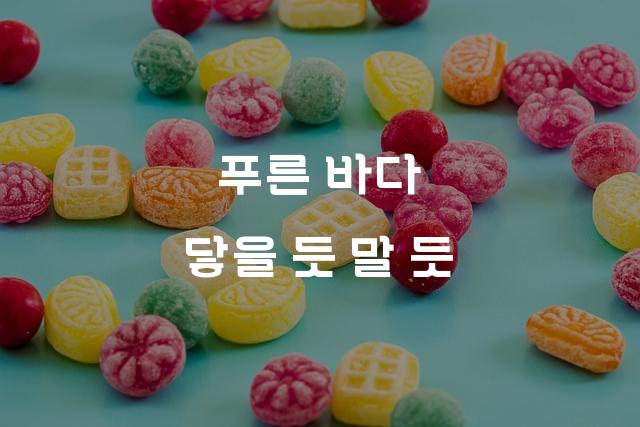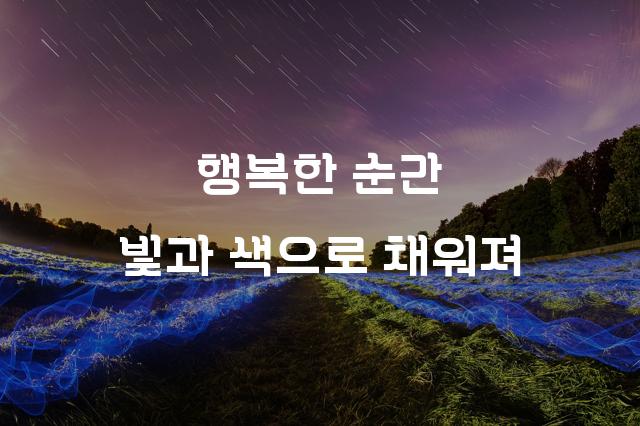
길벗체 TG는 비온뒤무지개재단에서 제작한 꽉 찬 고딕 스타일의 폰트로, 장식적 요소가 가미된 장식체 디자인을 특징으로 합니다. 이 폰트는 현대적 감각과 전통적 느낌을 조화롭게 결합해 독특한 시각적 경험을 제공합니다.
길벗체 TG은(는)
기본 고딕, 굵은 고딕, 장식 스타일, 단단함, 별모양/패턴 계열의 생김새를 가지고 있으며
웹/앱 디자인, 프레젠테이션, 보고서/문서 등에서 자주 활용되며, 효과적인 메시지 전달에 적합합니다.
이 폰트는 교육, 기술/IT, 금융/비즈니스 분야에 잘 어울리며,
신뢰감, 명확한, 전문적인 느낌을 담고 있는 것이 특징입니다.